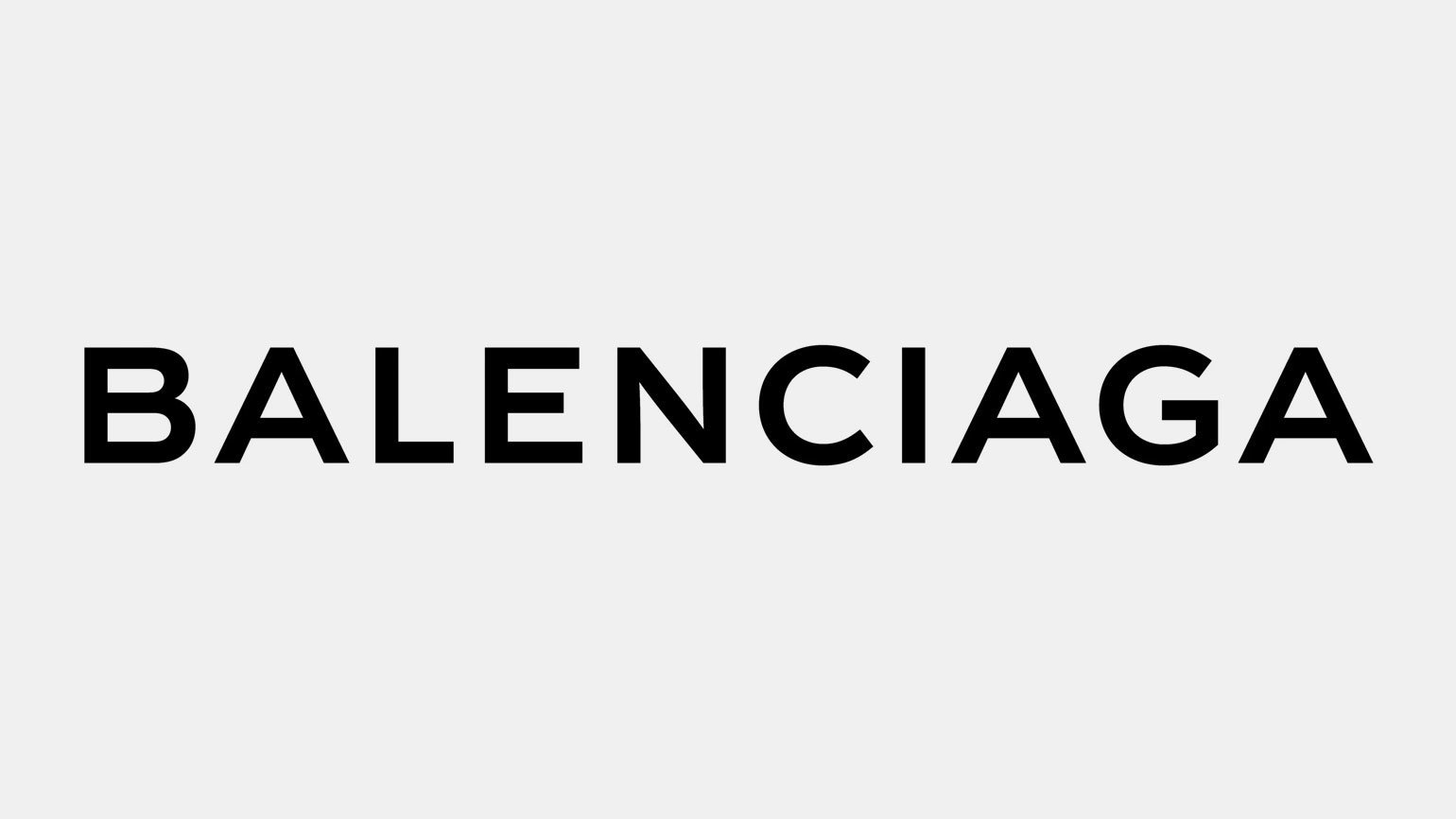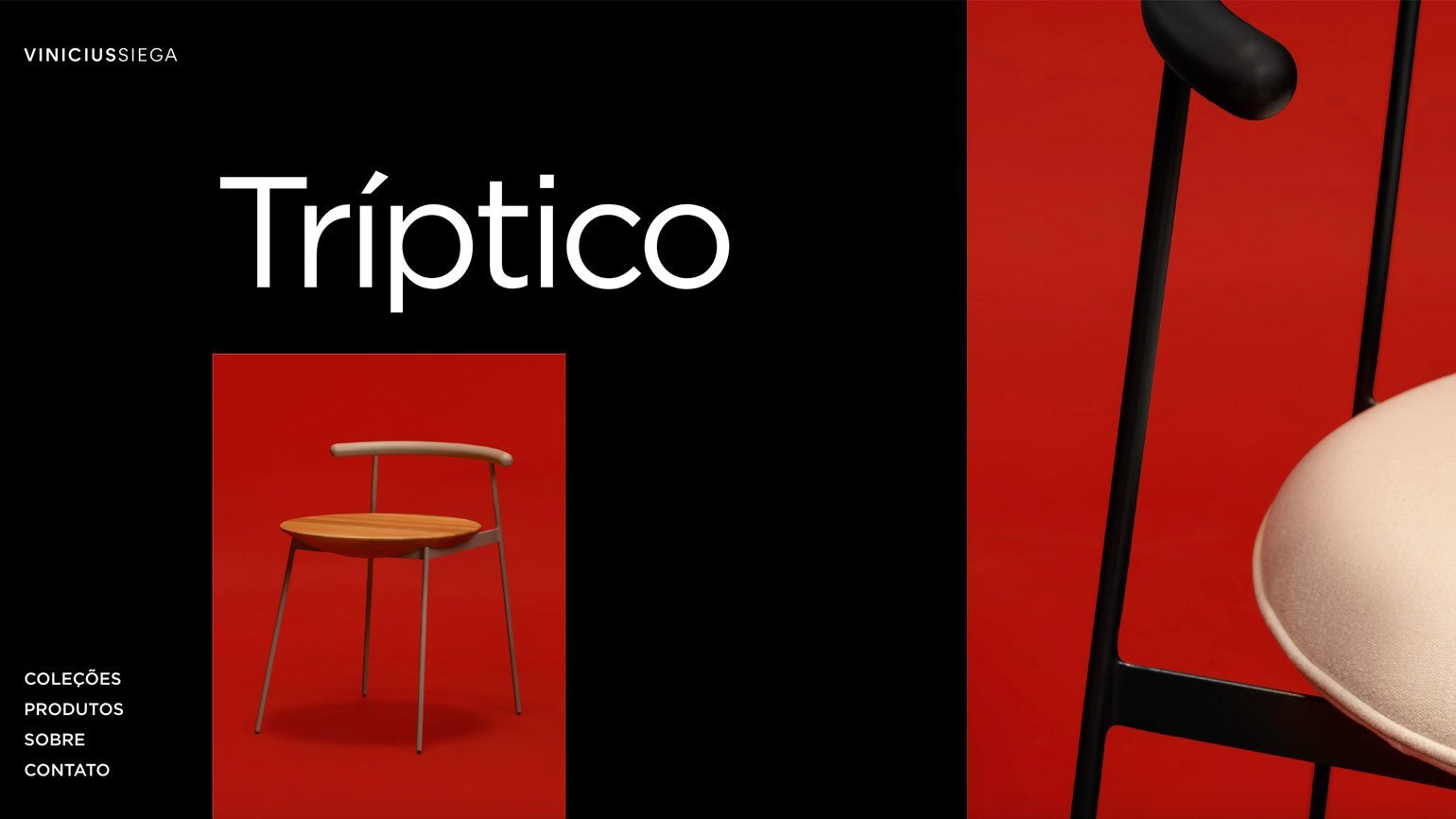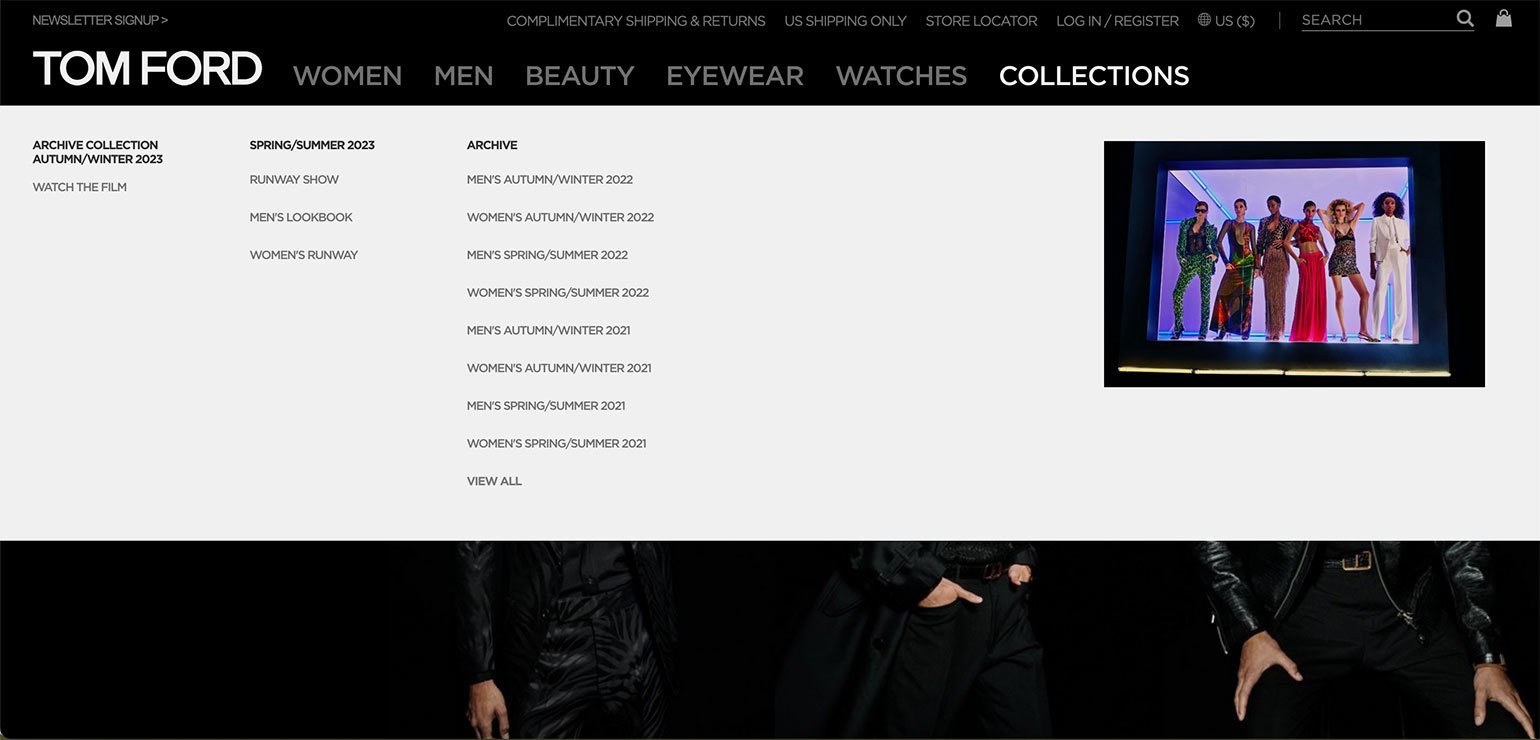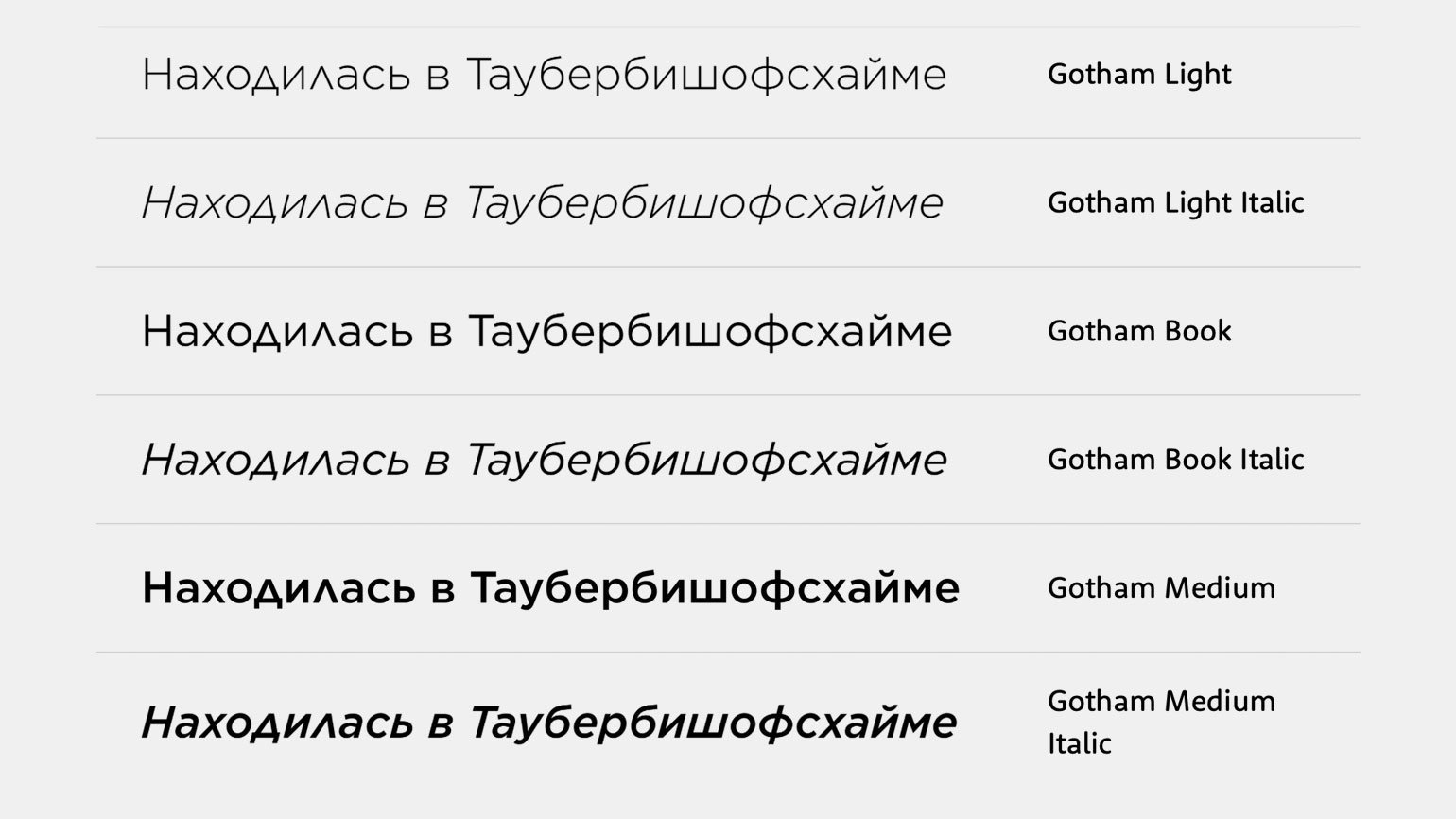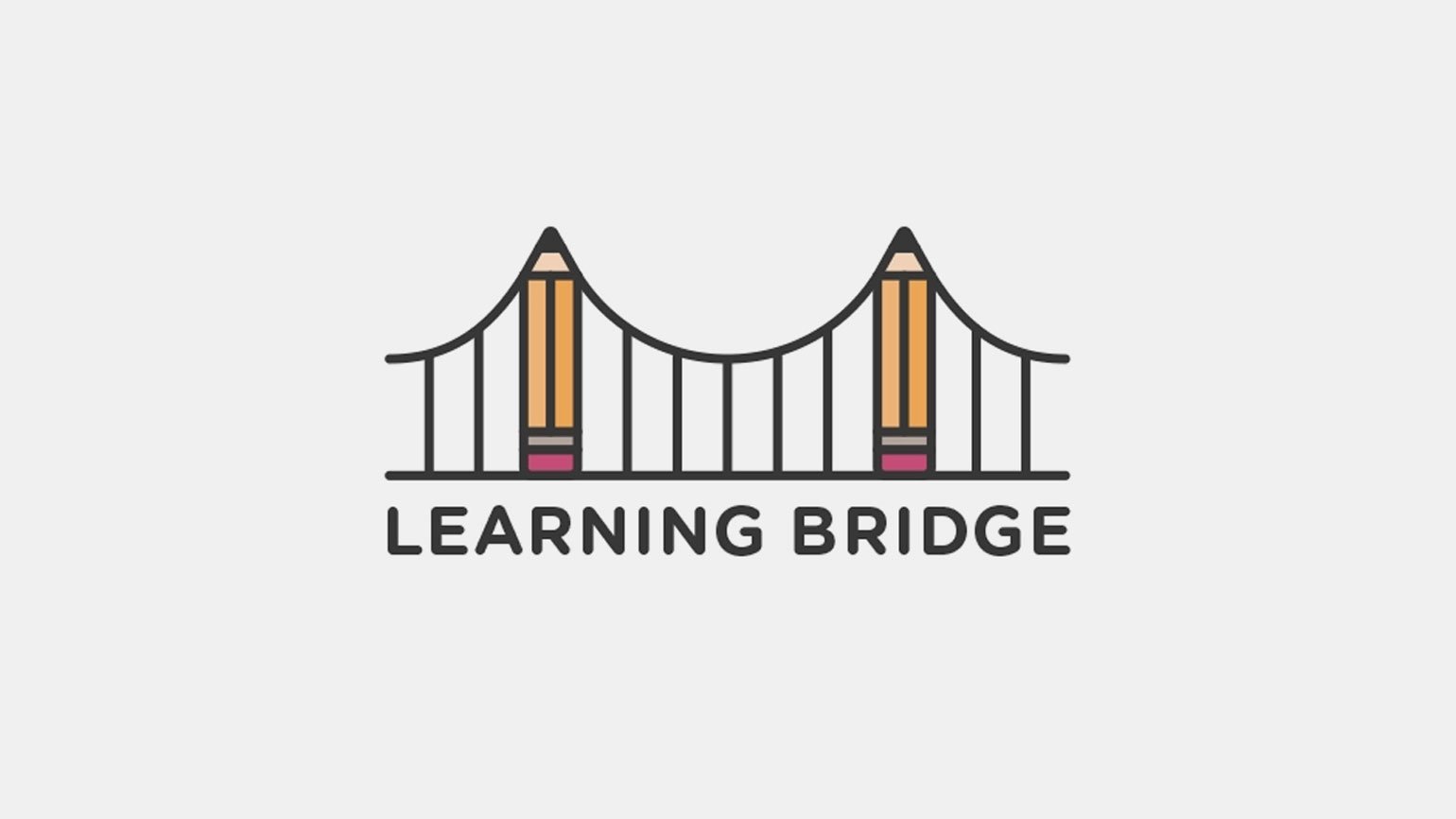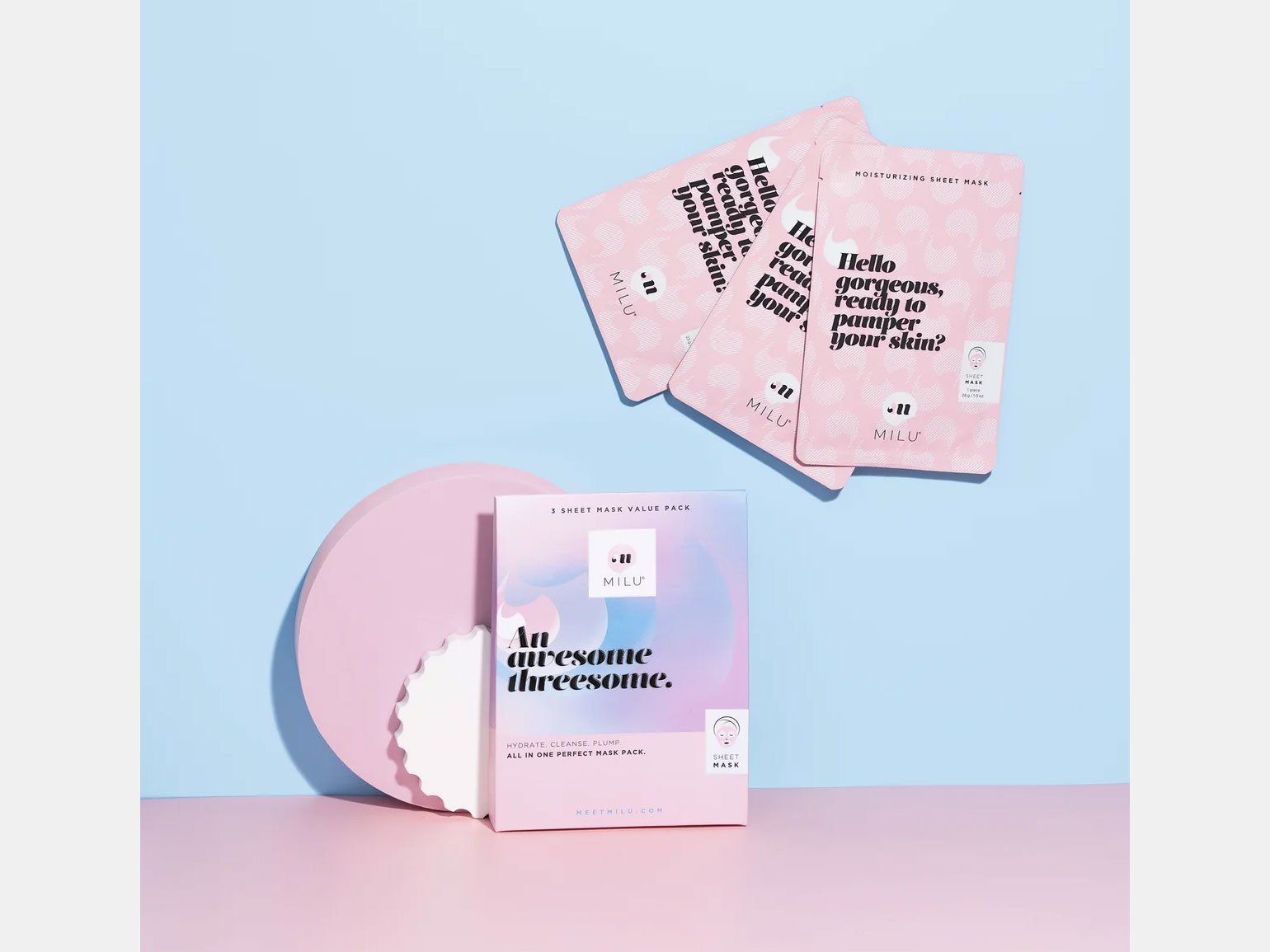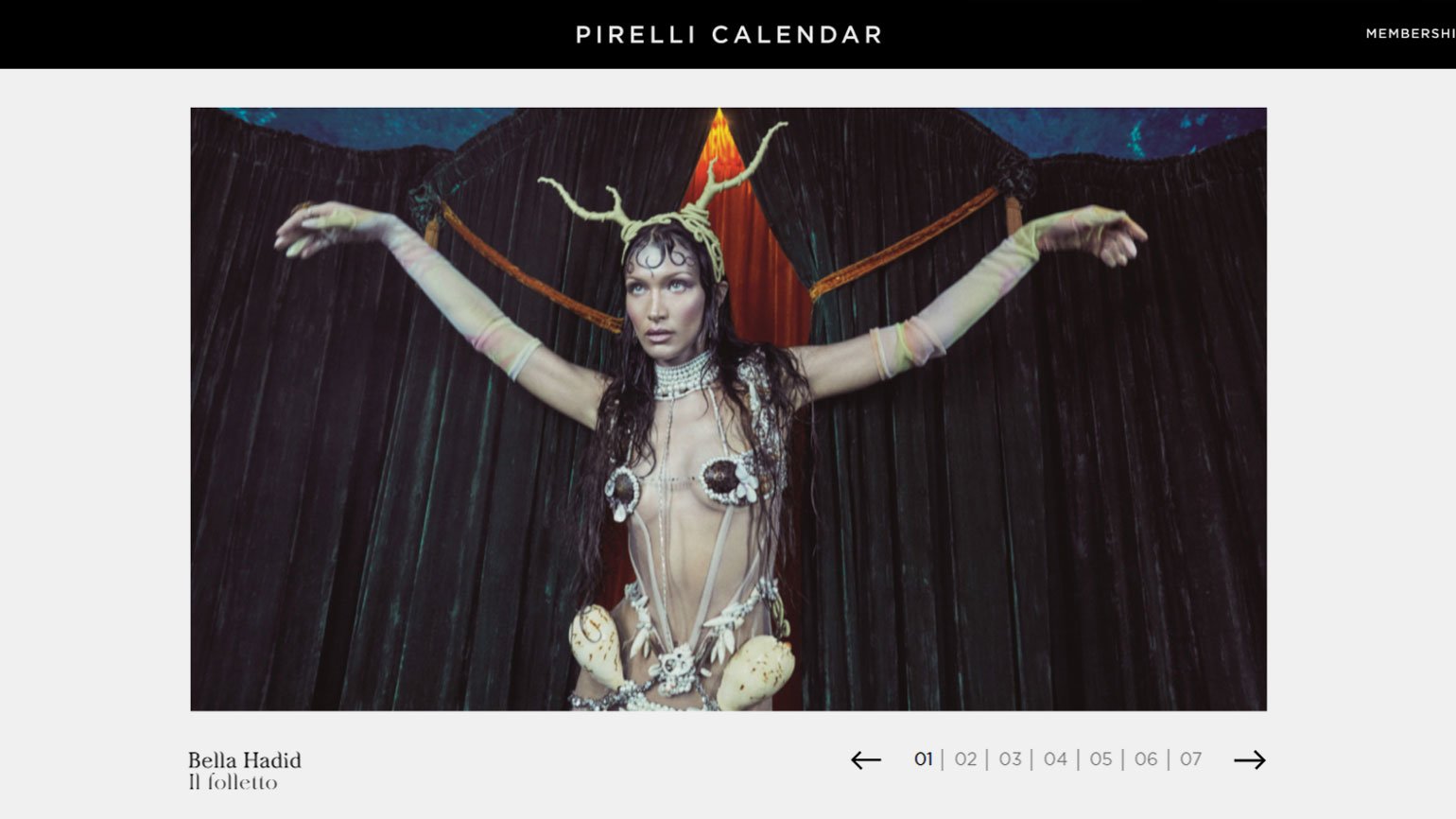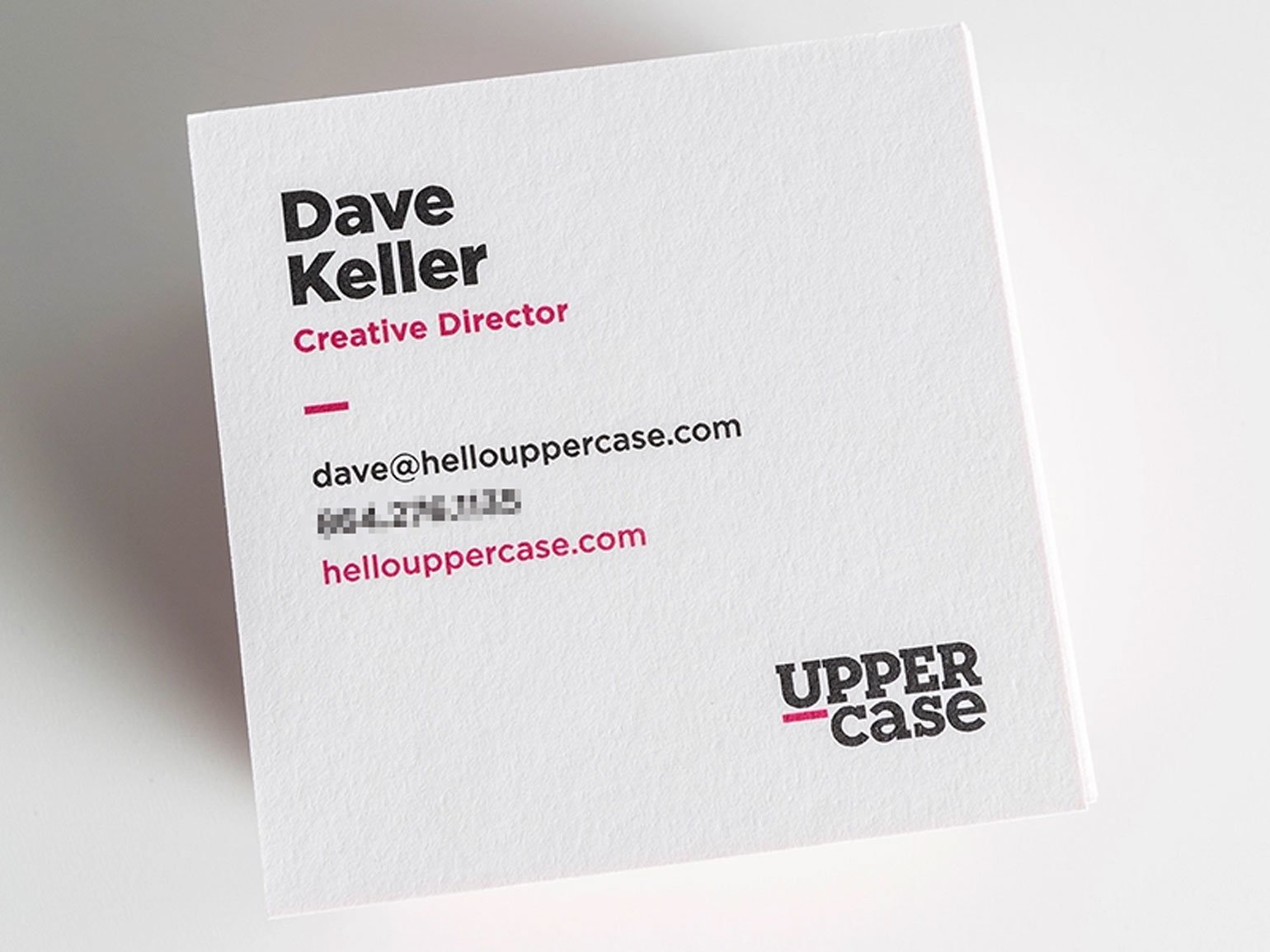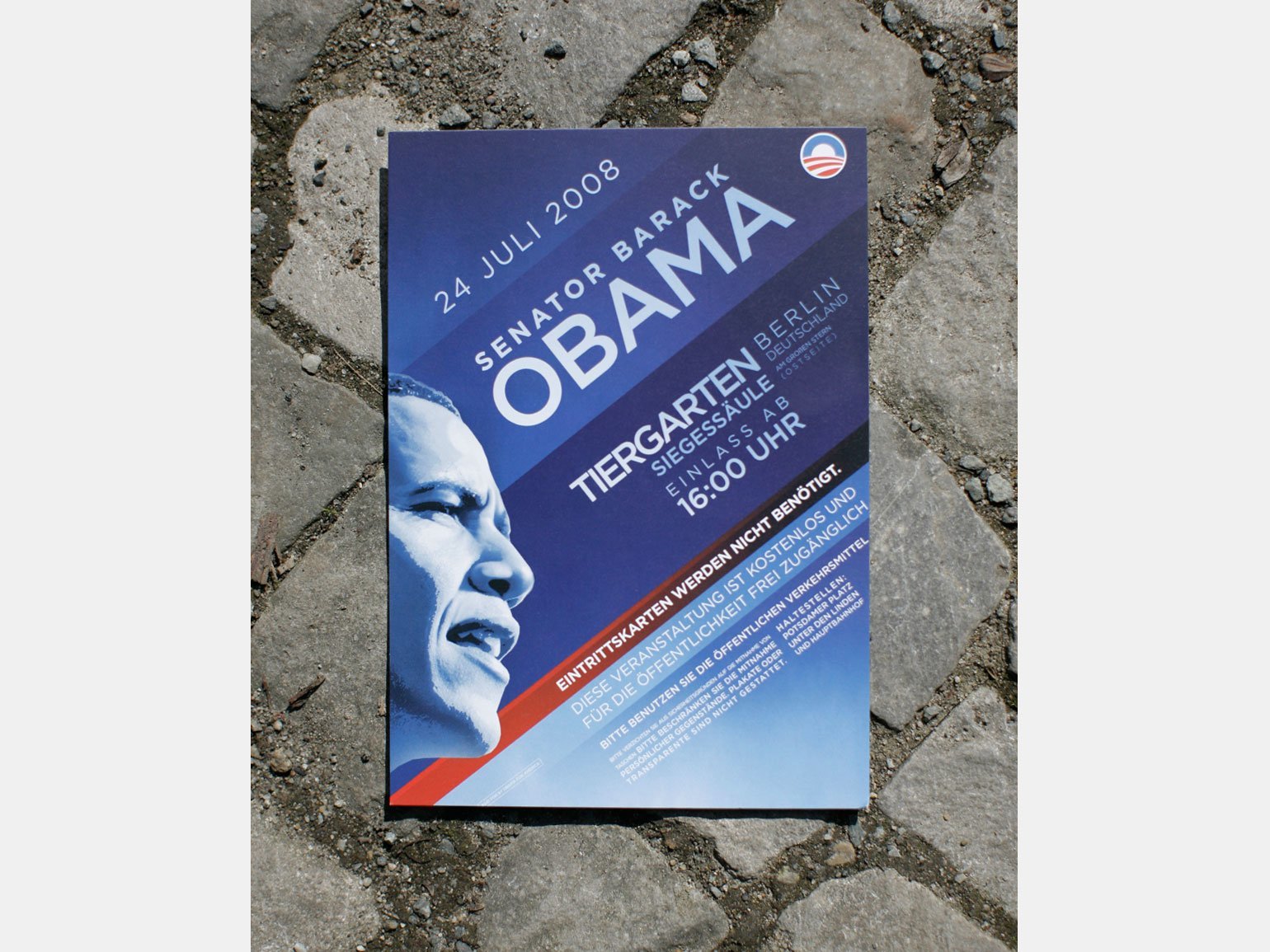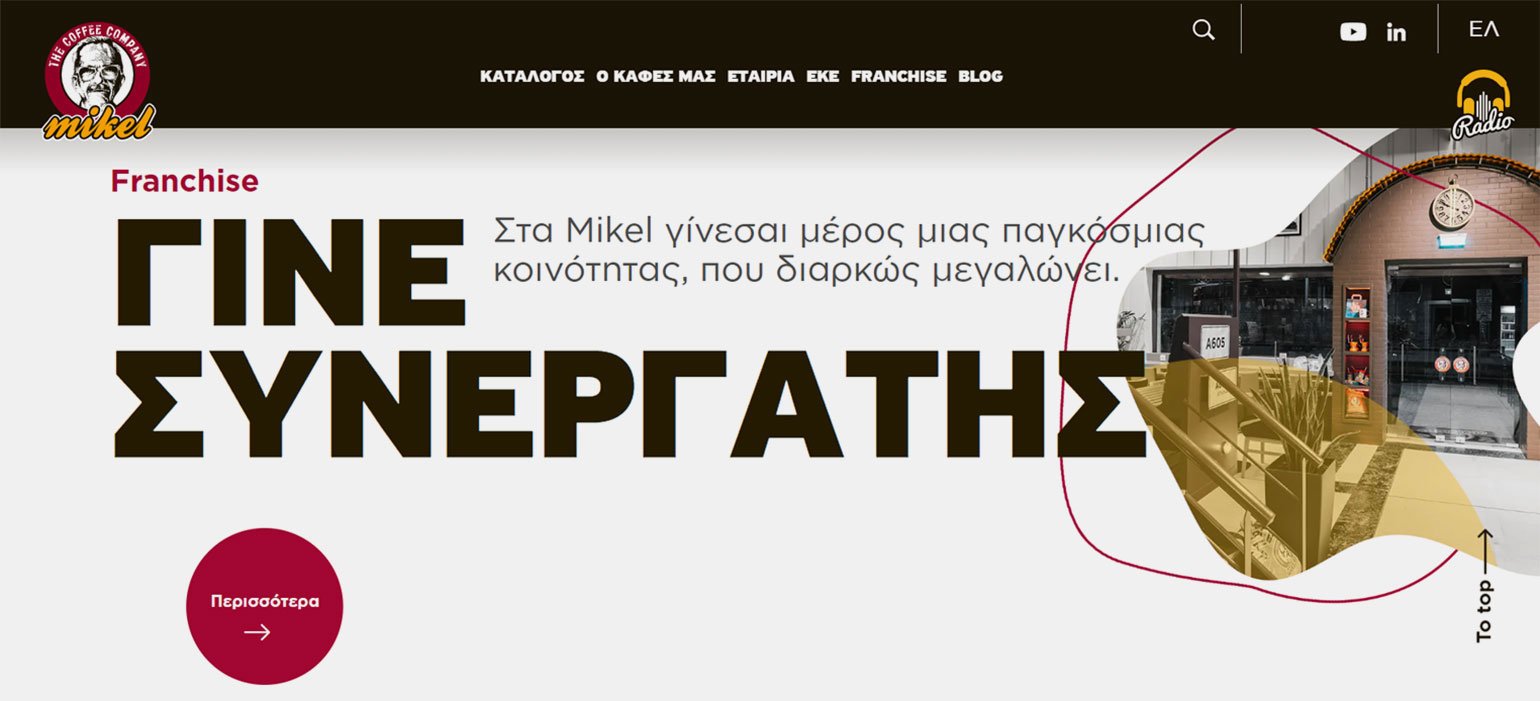
Шрифт Gotham: где используют и с чем сочетают
Рассказываем, для каких проектов подходит Gotham, и показываем примеры удачных шрифтовых пар с ним.
Создать эффектную типографику для сайта, документа, постера или рекламы непросто. Правильное решение очень важно: шрифты влияют на восприятие текста и изображений, они способны и привлекать, и отталкивать. К тому же их много, и даже если для проекта уже выбран основной шрифт, к нему наверняка понадобятся дополнительные.
Разберём одну из популярных гарнитур — Gotham — и расскажем, с чем её сочетать.
Gotham — что это за шрифт
Гарнитура Gotham вышла в 2000 году. Заказчиком этого дизайн-проекта стал журнал GQ, и задача звучала как «создать современный, рациональный шрифт».
Изначально одного из её авторов, Тобиаса Фрер-Джонса, вдохновило особенное оформление табличек в автобусном терминале на Манхэттене. Но всё же за дизайном гарнитуры стоит большое исследование нью-йоркских уличных знаков навигации и бытового городского леттеринга, которое он провёл вместе с коллегой, Джонатаном Хофлом.
Референсами для дизайна послужили вывески магазинов, реклама, указатели, оформленные красками и неоновыми трубками, отлитыми в металле и вырезанными в камне. В Нью-Йорке явно существовал особенный, типичный рисунок букв, но у него не было имени и он не был оформлен в систему. Поэтому новый шрифт Gotham, который появился в результате этой работы, стали воспринимать как что-то естественное, базовое.
Более того, он «вернулся» в город, который его породил: с 2002-го, когда набор вышел на рынок, Gotham стали массово использовать в дизайне обложек, сайтов, рекламы и вывесок. Именно им оформлен текст на мемориале на месте башен-близнецов в Нью-Йорке. Но главным звёздным моментом Gotham стала президентская кампания Барака Обамы 2008 года: в основе её айдентики была эта гарнитура.
Теперь Gotham считают классикой американского шрифтового дизайна, и он даже внесён в реестр объектов MoMA.
В течение нескольких лет после выпуска Gotham команда студии Hoefle & Co продолжала добавлять насыщенности в гарнитуру и расширять её знаковый состав. Сейчас это уже суперсемейство, в которое входят:
• 66 шрифтов семейства Gotham — 33 насыщенности от Thin до Ultra в начертаниях от Extra Narrow до Regular и соответствующие им курсивы;
• 8 шрифтов семейства Gotham Rounded.
Gotham поддерживает расширенную латиницу, кириллицу, греческий язык.
Так выглядит кириллица Gotham
Предыдущий вариант логотипа Balenciaga, с 2013 по 2017 год, был набран Gotham
В типографике официального сайта Tom Ford использован Gotham
Gotham Rounded в логотипе для образовательного стартапа
Несколькими вариантами Gotham оформлены и логотип дизайнера мебели, и тексты на сайте. Для декоративных целей одну i в слове Triptico заменили на букву с акутом — диакритическим знаком ударения. Этот глиф тоже входит в кассу шрифта
Gotham в интерфейсе
Шрифтовая пара Gotham и Ninna
Тема календаря Пирелли на 2023 год — «Любовные письма к музам»: на его страницах 14 моделей, снятые в образах покровительниц искусств и творчества. Это настроение в дизайне сайта поддерживает орнаментальный шрифт Ninna, пару которому составляет Gotham.
Последний выбран не просто как шрифт, который хорошо работает в веб-дизайне: Gotham связывает два отдельных цифровых продукта — сайт календаря и официальный сайт Pirelli, где он также использован в интерфейсе.
Шрифтовая пара PF Highway Sans Pro и Gotham
Скриншот: сайт Mikel / Skillbox Media
Типографика сайта греческой сети кофеен построена на сочетании Gotham и PF Highway Sans Pro. Рисунок второго гротеска тоже основан на дизайне американской навигации — дорожных знаках, стандарт оформления которых приняли в 1966 году.
PF Highway Sans Pro вышел примерно тогда же, когда и Gotham, — в 2001 году, а создал его греческий дизайнер Panos Vassiliou.
Gotham в упаковке
Шрифтовая пара Salome Stencil и Gotham
Изображение: Milu
Логотип косметической марки Milu оформлен Gotham Light, а надписи на упаковках — сочетанием Gotham Light, Gotham Book и акцидентного шрифта Salome Stencil.
Salome придаёт дизайну лёгкое, игривое настроение, что особенно заметно на контрасте с «рациональным» Gotham.
Gotham в айдентике
Шрифтовая пара Gotham и брусковая антиква
Простая айдентика с американским визуальным характером для небольшой дизайн-студии: Gotham для текстов и логотип, набранный брусковой антиквой.
Gotham в визуальных коммуникациях
Gotham в визуальной системе для кампании Барака Обамы